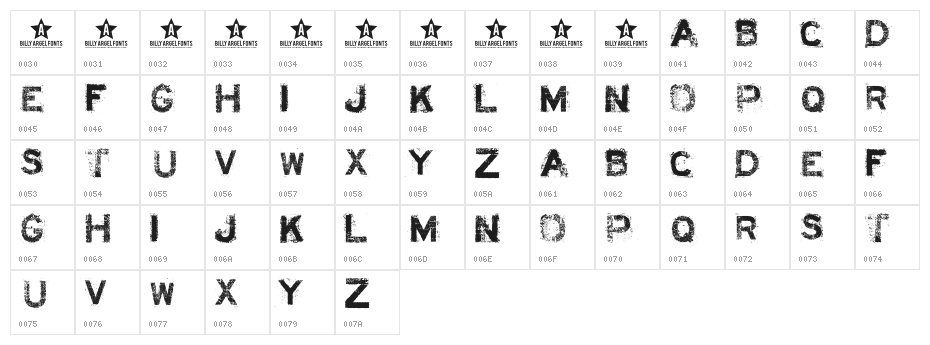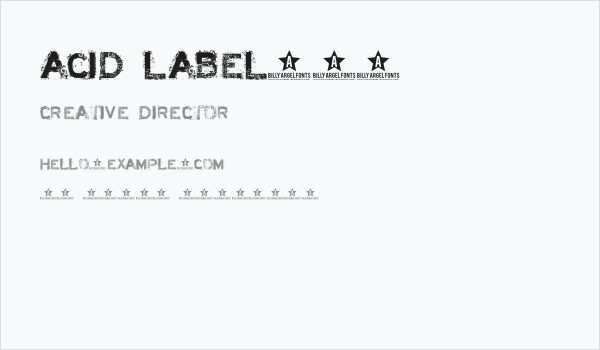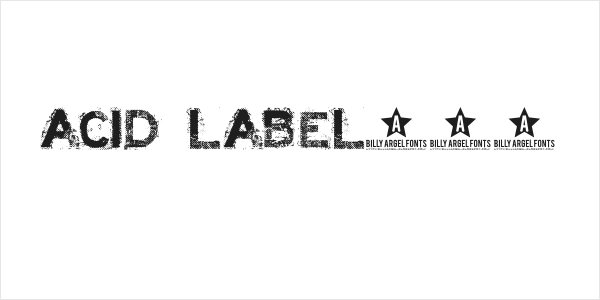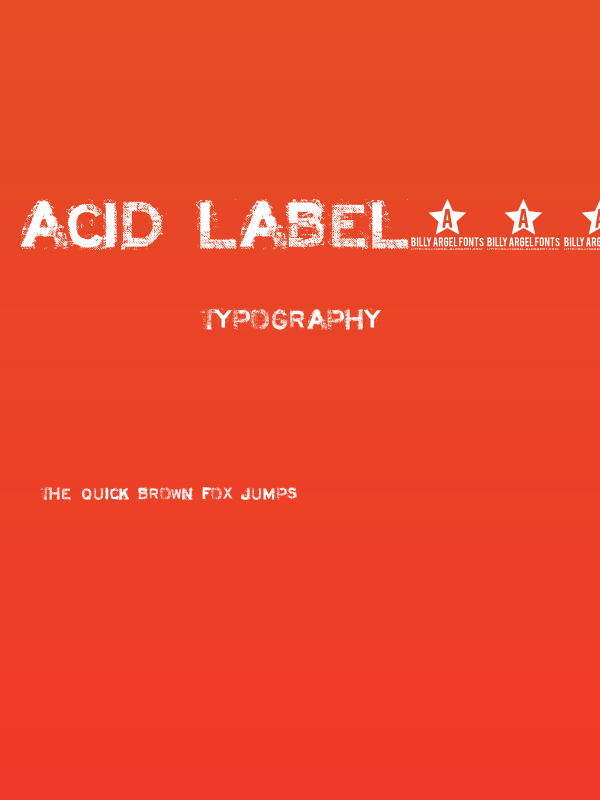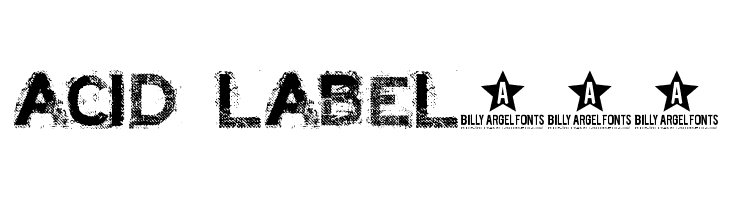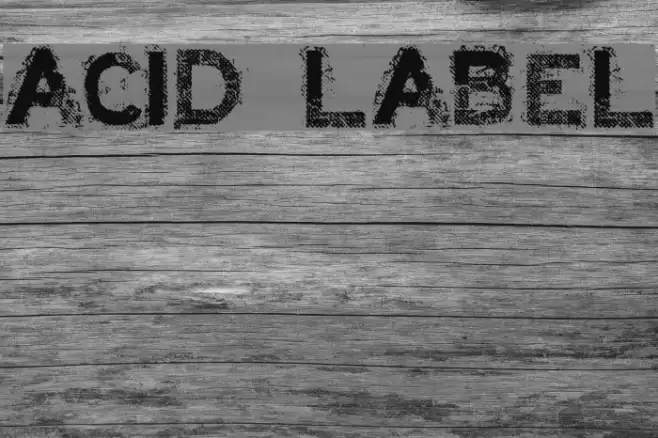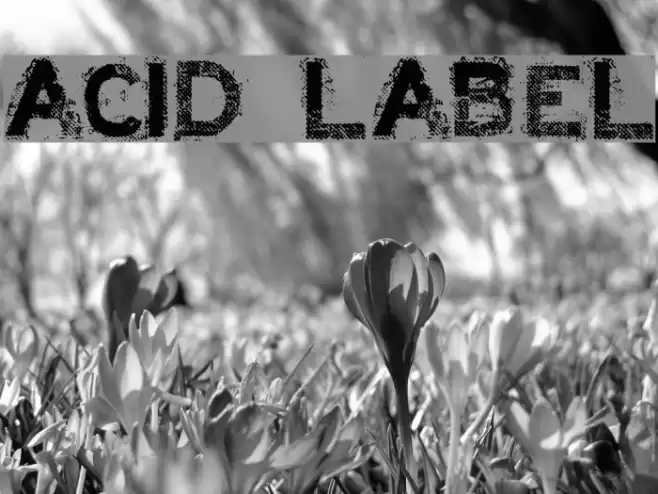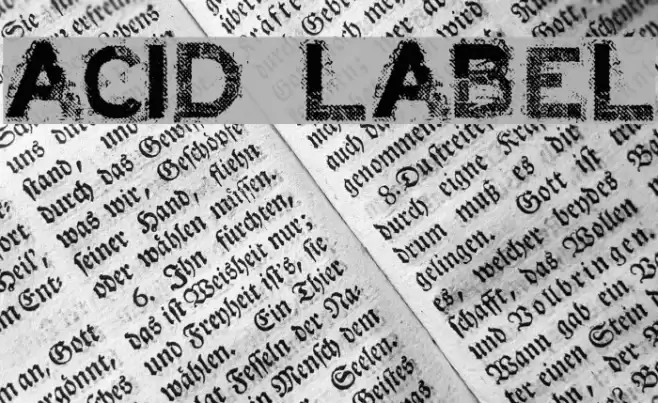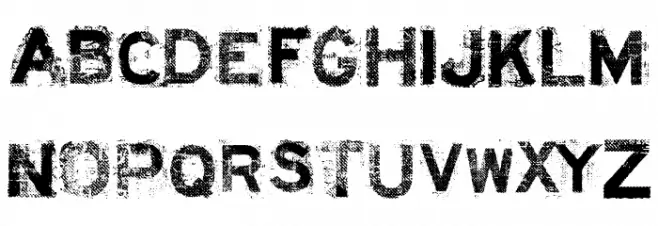
ACID LABEL___ Font
✎ Distorted Eroded
| Catégories | Distorted Eroded |
| Style général | Grunge, Industrial |
| Projets proposés | Ideal for album covers, posters, urban-themed designs, and branding that requires a gritty, edgy look. |